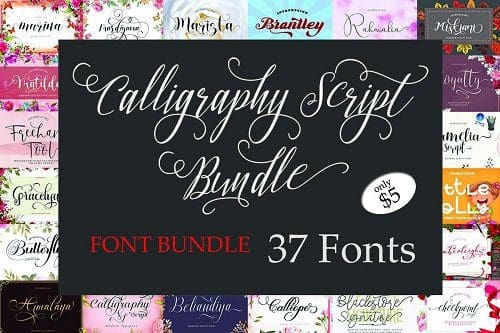
Calligraphy Script Font Bundle
تجمع هذه الحزمة 37 خطًا فريدًا في 27 خطًا.
تتضمن هذه الحزمة مجموعة متنوعة من أنماط الخطوط مثل الخط والتوقيع وحروف الفرشاة والكتابة اليدوية وغيرها الكثير. مع مئات الحروف الرسومية ، بما في ذلك البديل ، والأحرف المركبة ، والشرط ، ودعم اللغة الدولية.